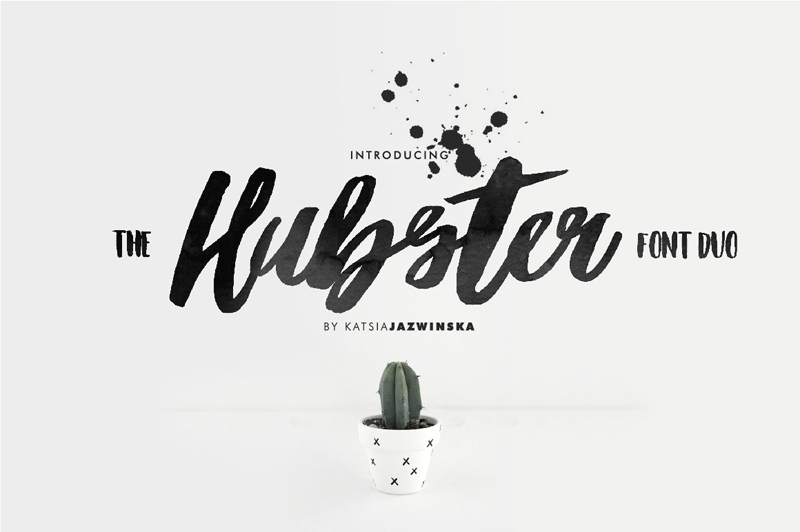
Hubster Script Font – Fonte Grátis
Hubster Script Font
Introduzimos Hubster, uma fonte dupla em caligrafia à mão cheia com forte personalidade e habilidades únicas. Esta foi criada para aqueles que adoram a arte na composição de letras. Hubster é perfeita tanto para designers profissionais quanto para amadores que desejam dar um toque único às suas criações. Com uma mistura única de estilo artístico e casual, este design permite criar letras impressionantes em poucos cliques. Ideal tanto para textos estilizados quanto para nomes ou logotipos, Hubster inclui todas as letras maiúsculas e minúsculas necessárias, pontos de interpolação, números e caracteres especiais europeus. Além disso, oferece uma versão em formato de letras maiúsculas com opções, tornando-o ainda mais funcional para diferentes necessidades de design. Com Katsia Jazwinska como designer, a Hubster vem pronta para ser o seu aliado na criação de textos artísticos e inovadores.
Designer: Katsia Jazwinska